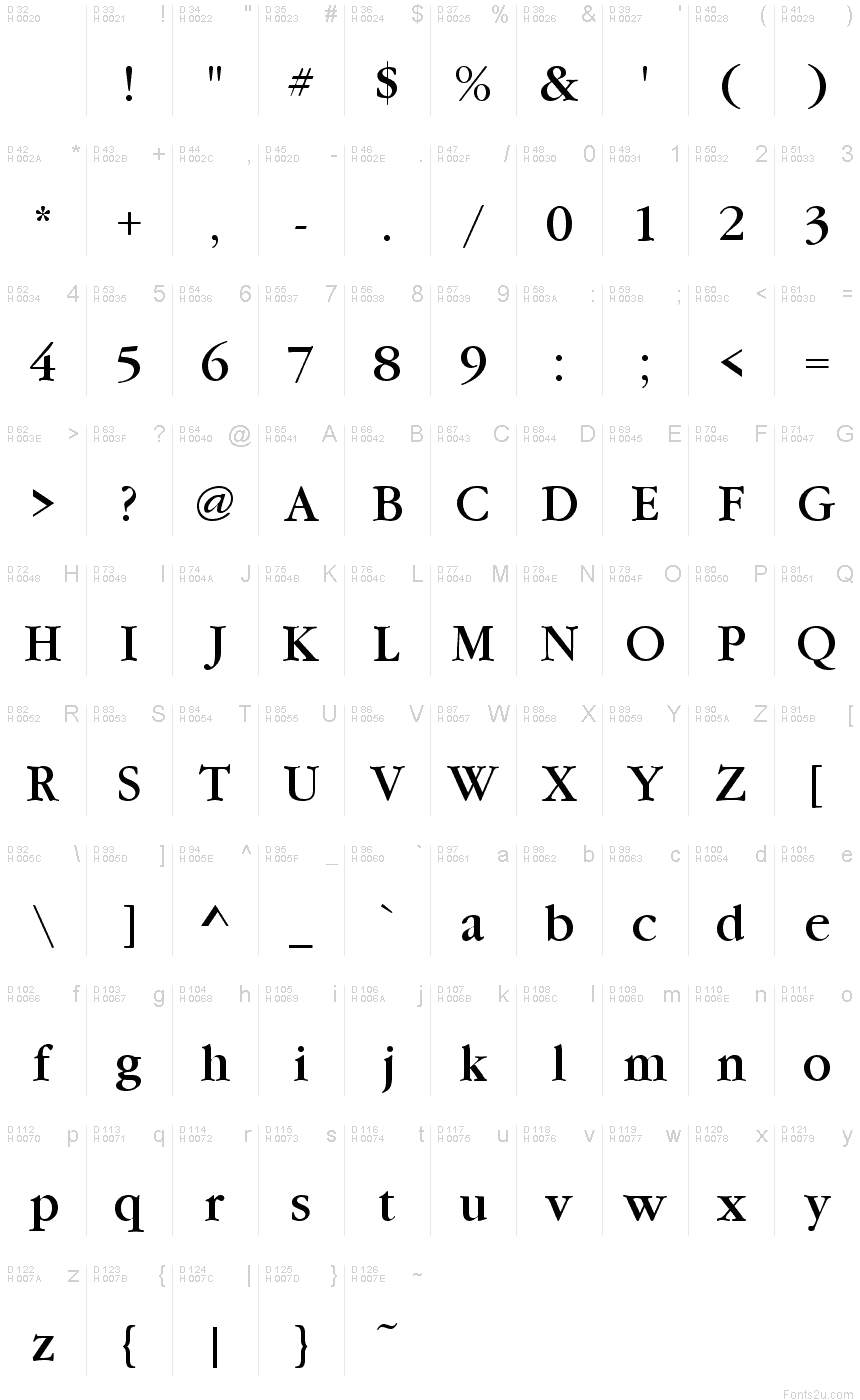
Gourmand
Gourmand, creata da MGI Software, è un carattere serif gratuito dal fascino ricco e corposo, che sembra uscito direttamente dal menu di un ristorante d'altri tempi o da un'etichetta di vino vintage. Le sue curve ampie e arrotondate, unite a tratti leggermente svasati, donano a ogni lettera un peso solido e artigianale, mentre la spaziatura compatta rende le parole dense e piene di carattere. Le sue forme possiedono un fascino discreto che richiama cene a lume di candela, tovaglie di lino e piatti presentati con cura.
Con Gourmand puoi aggiungere un tocco di eleganza artigianale a loghi di ristoranti, packaging, menu, copertine di libri di cucina, inviti o progetti di branding ricercati. Questo font gratuito dà il meglio di sé nei formati grandi, dove i suoi dettagli scolpiti possono risaltare; abbinalo a un carattere sans serif geometrico pulito per i testi di supporto, così da mantenere un layout raffinato e leggibile.